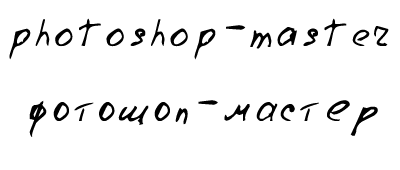
Шрифт - Lazy Crazy
Интересный шрифт, который хорошо подходит для работы в фотошопе. Есть поддержка русского языка.
Забавный шрифт
это ж копия моего почерка.
мой почерк =_=
на мои каракули чем-то похож. Замечательный шрифт
у меня почерк такой
раздельно пишу, не соединяю буквы
Очень похоже на мой почерк. =)
мой почерк в понедельник на первом уроке :)
А мне нравится и даже никакого криворукого лентяя, по моемй изящный=))
Обожаю этот шрифт! Мне напоминает как будто кто-то нацарапал на 3аборе!